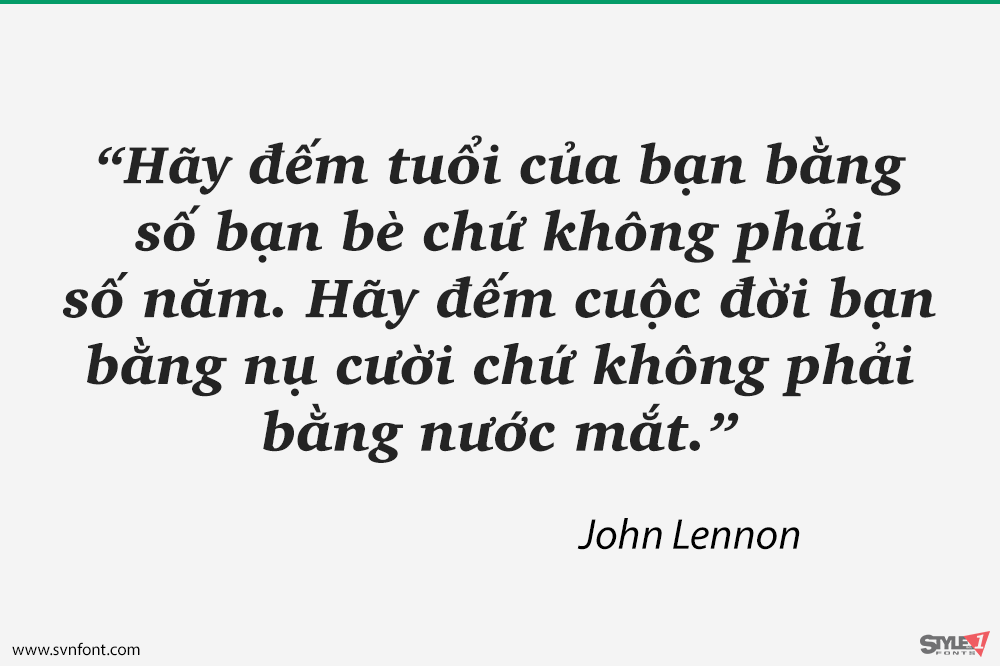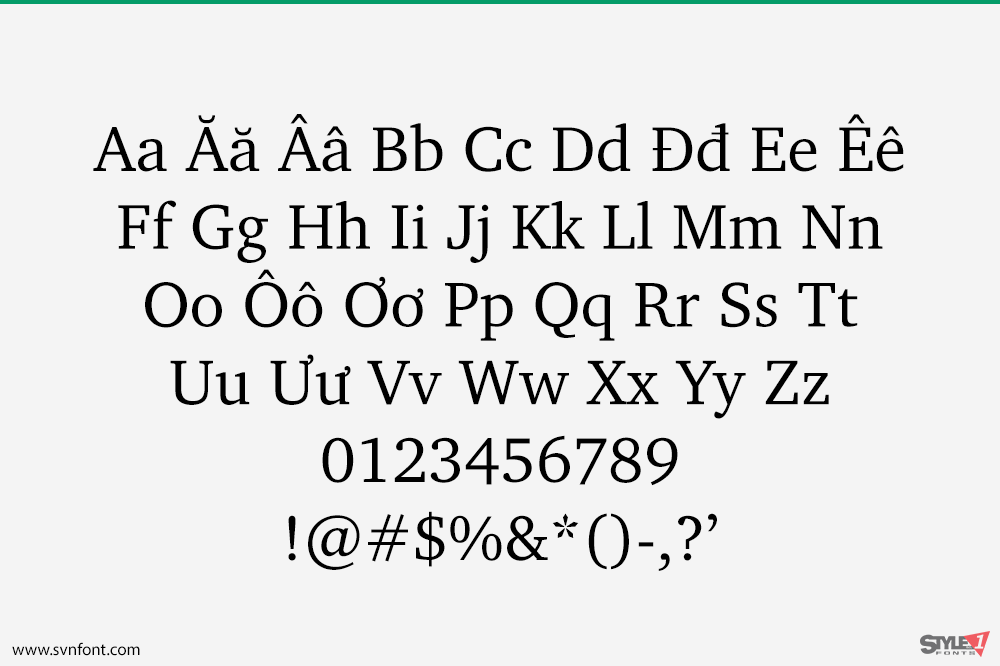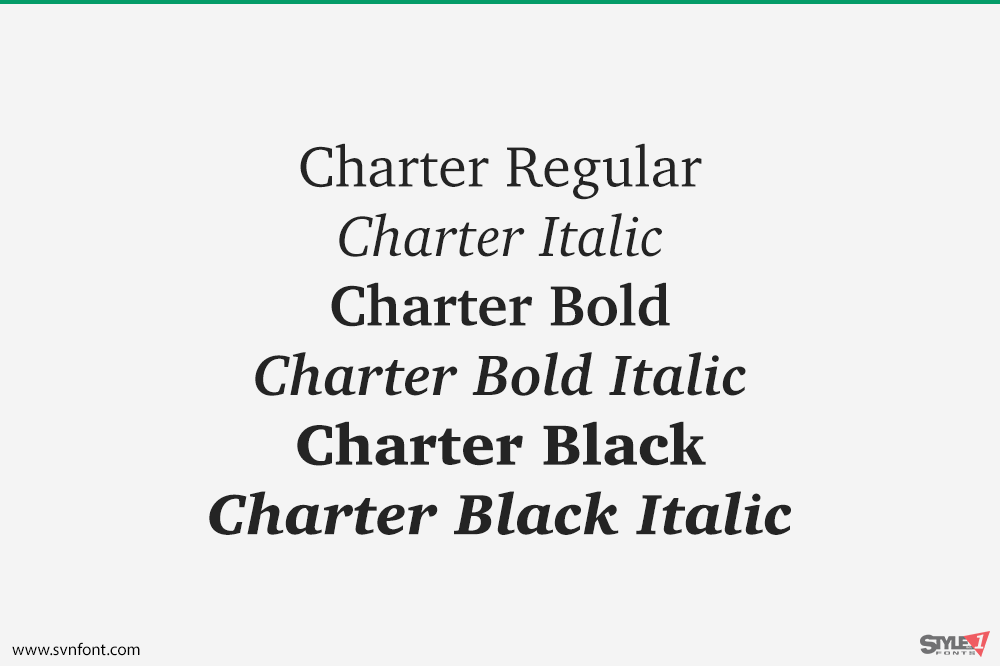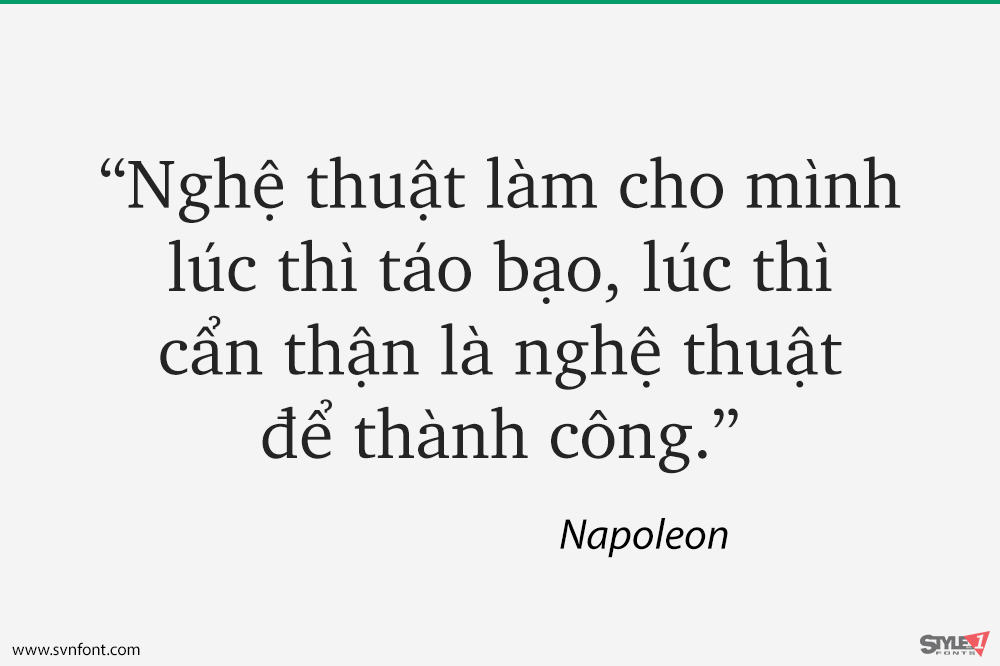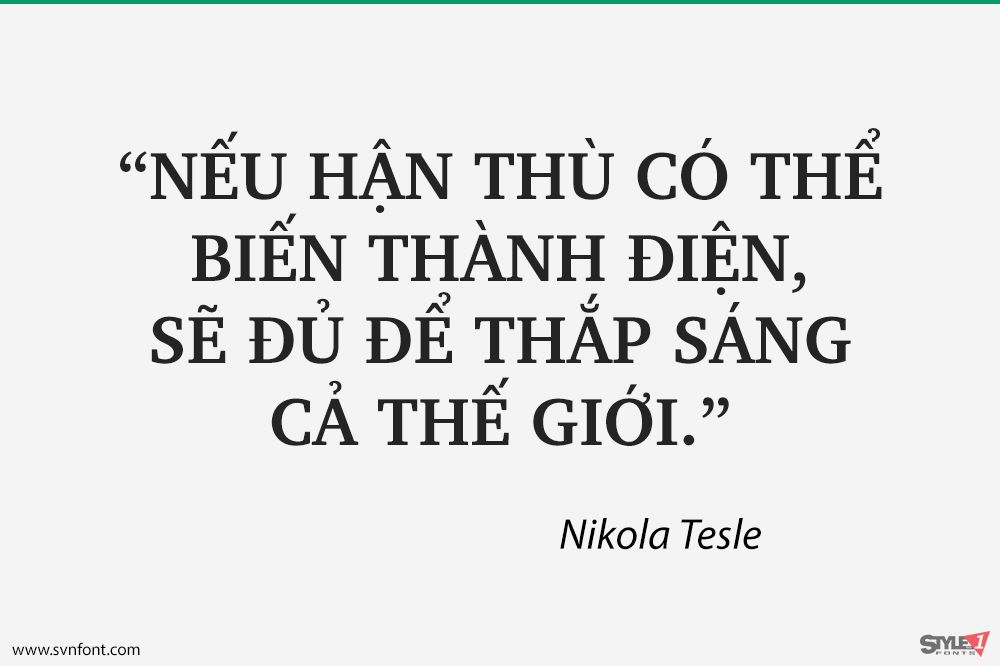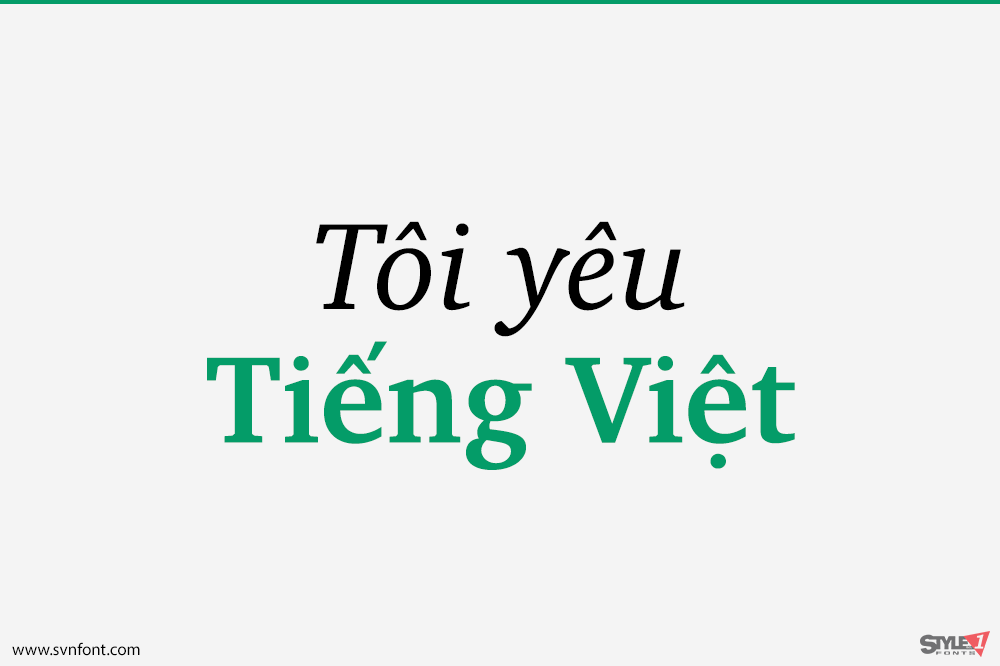
Charter được Matthew Carter thiết kế vào giữa những năm 1980. Kiểu chữ này được thiết kế có tính đến những hạn chế của các thiết bị xuất bản có độ phân giải thấp và trung bình; vì thế các nét serif được làm vuông vắn và các đường chéo, đường cong được tiết kiệm. Tuy nhiên, thiết kế này ngay lập tức thành công nhờ vào những ưu điểm của chính nó.
Đây là một phông chữ tuyệt vời để sử dụng hàng ngày cho nhiều mục đích khác nhau, bao gồm sách và sách hướng dẫn kỹ thuật. Charter cung cấp các bộ ký tự chữ in hoa nhỏ, mở rộng và thay thế giúp nó trở nên linh hoạt và hữu dụng hơn. ITC đã mua lại thiết kế Charter vào năm 1993, nhưng Bitstream vẫn giữ quyền bán các thiết kế ban đầu.
Nhà thiết kế: Matthew Carter
Nhà phát hành: ITC Inc.